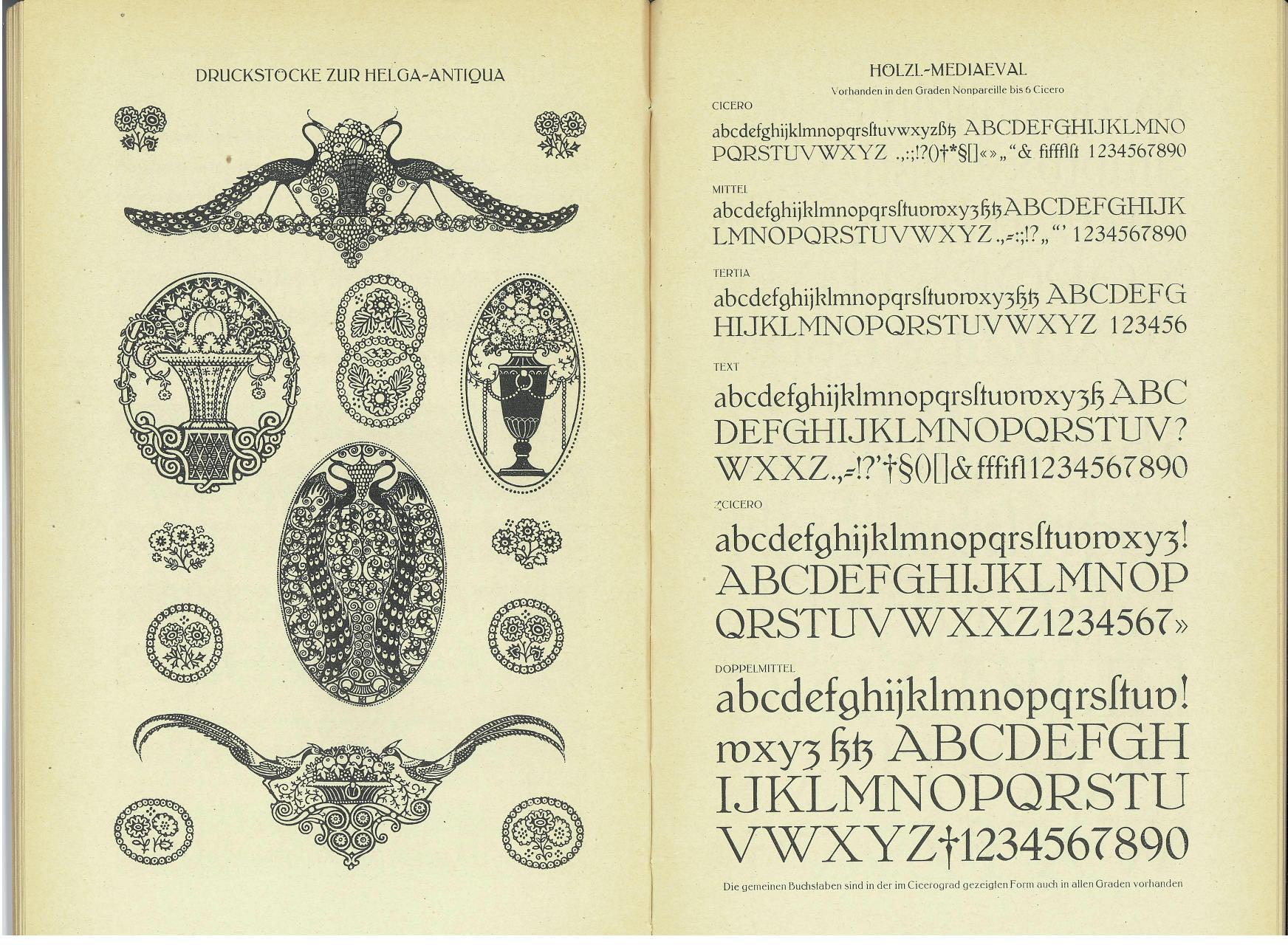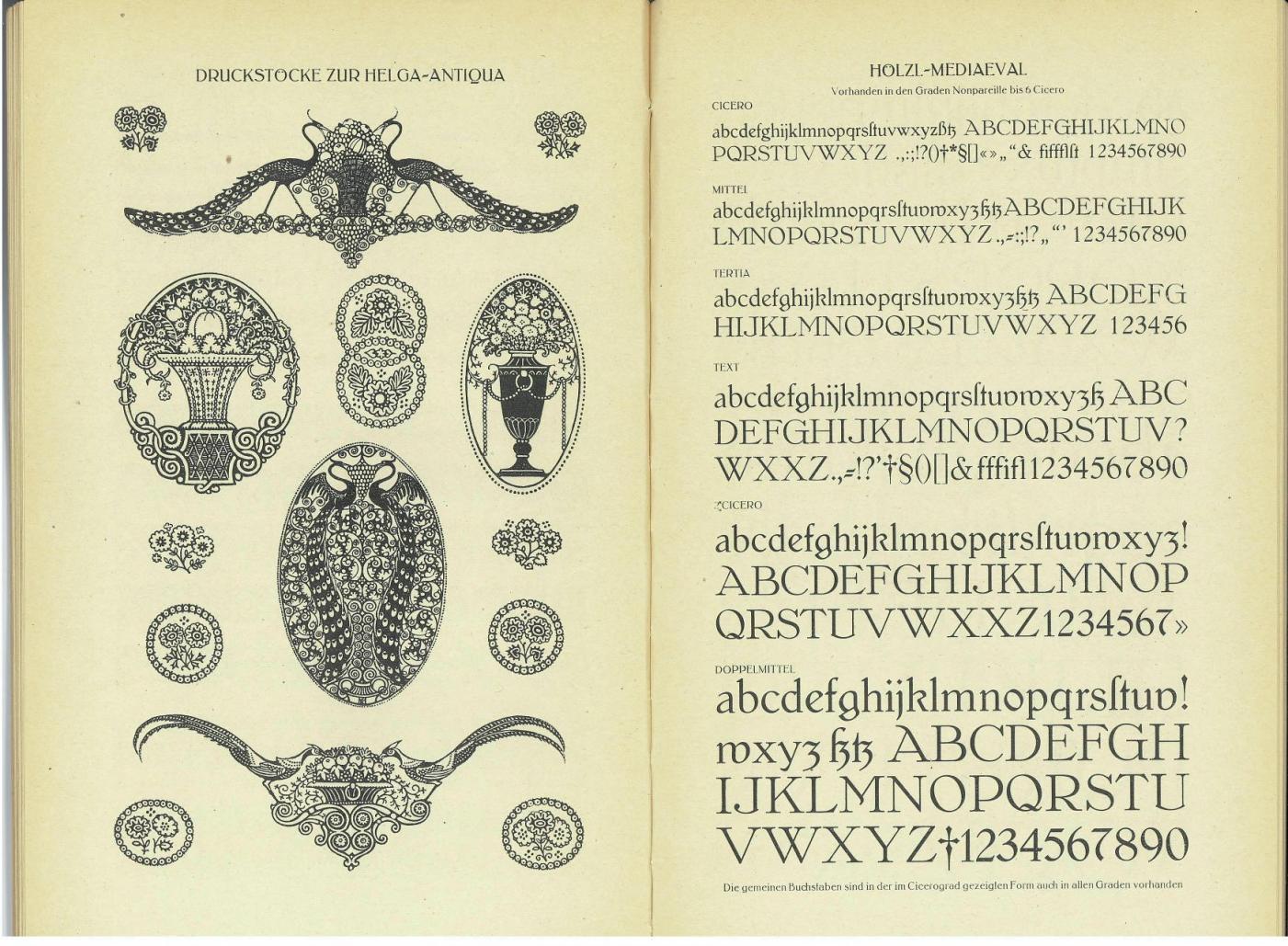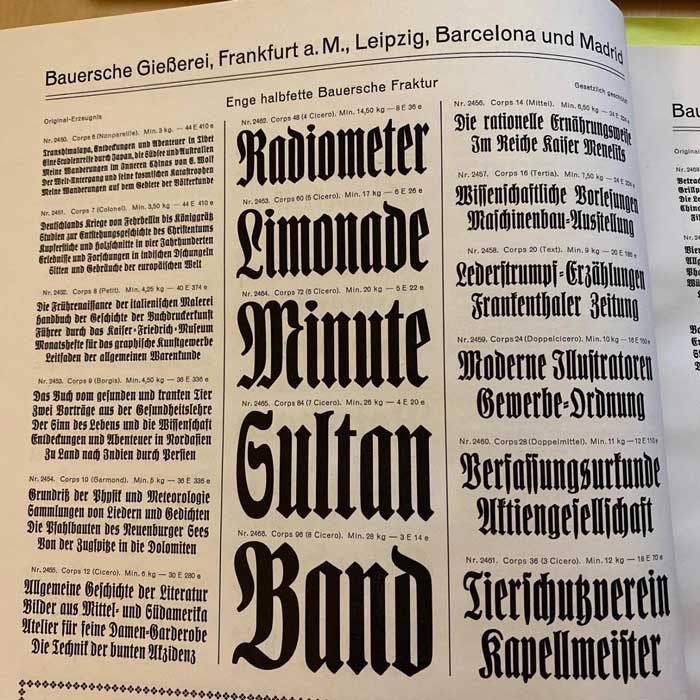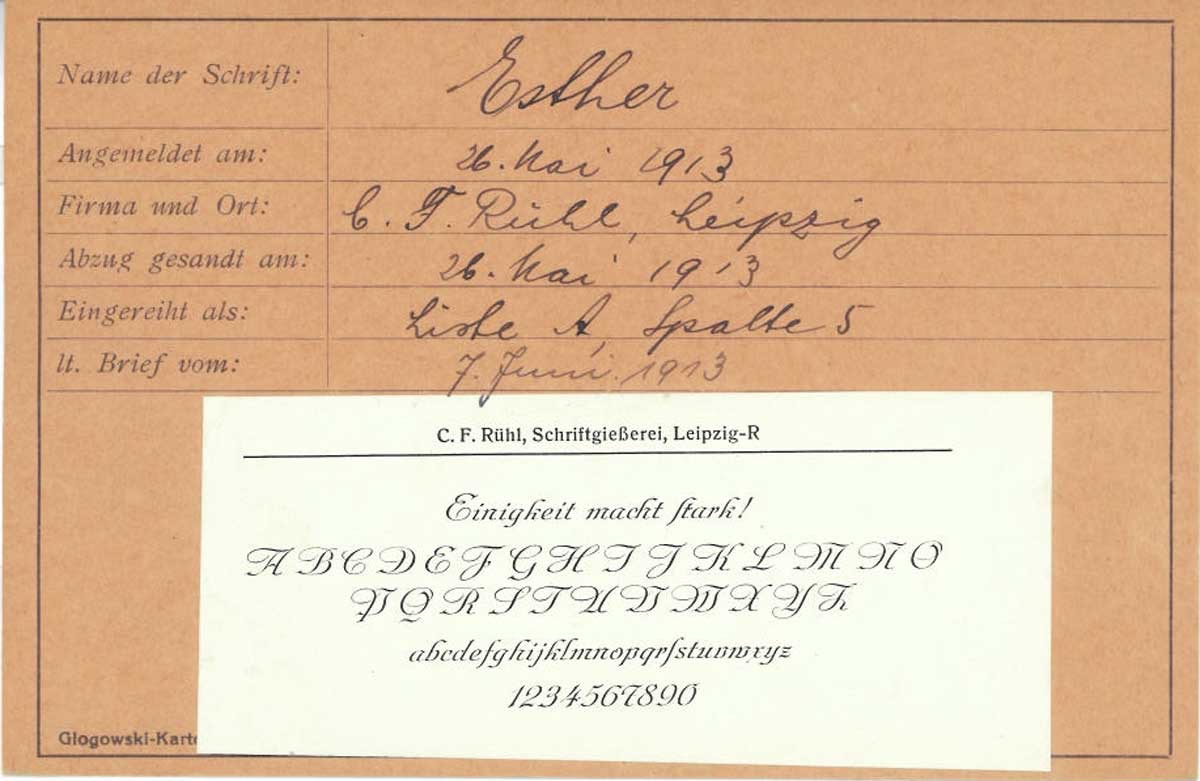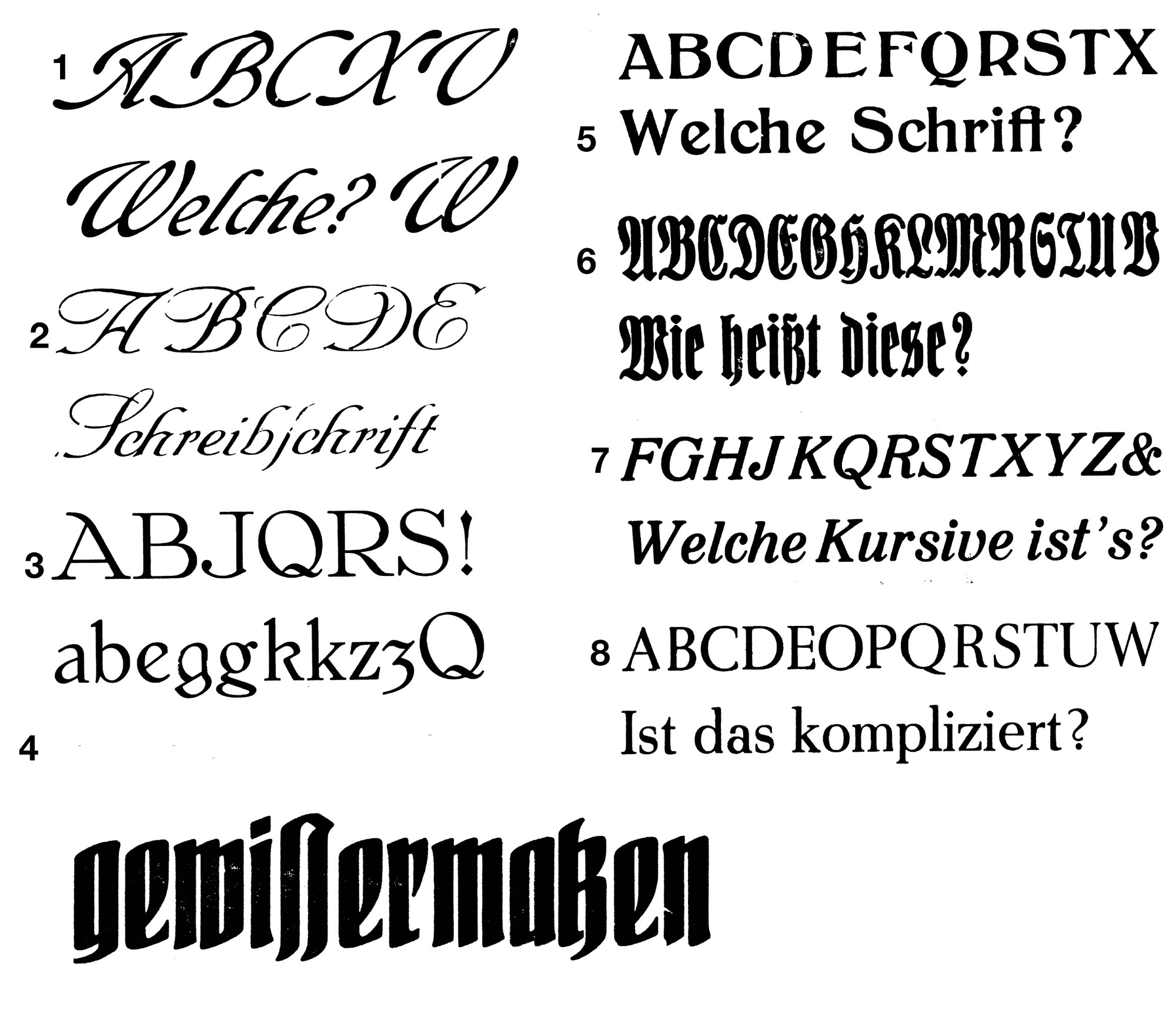
Vermutlich sehr alte Bleisatzschriften zum Identifizieren
mit diesen Schriften (aus vermutlich den Anfangsjahren des 20. Jahrhunderts) komme ich nicht wirklich zu einem Ergebnis bezüglich Schriftnamen, Gestalter, Herkunft ...
Es sind alles Bleisatzschriften in nicht wirklich tollen Zuständen, die aus verschiedenen Druckereien stammen, vorwiegend im süddeutschen Raum. Die erste ist möglicherweise die "Riedingerschrift", 3 und 5 vermutlich irgendwas aus der Ecke Ehmke/Belwe/Klinger und die 6 vermutlich irgendwas mit extraschmal und Anzeigenschrift oder so ...
Gelöst von Taurec
1 ist Riedingerschrift
Based upon Riedingerschrift, cut by Franz Riedinger for Benj. Krebs Succ. in Frankfurt am Main in 1906, here come Ridinger Std and its extended version, Ridinger Pro.
Nummer 2 ist die Esther der Schriftgießerei C. F. Rühl in Leipzig, später in den Bestand der H. Berthold AG übergegangen.
Nummer 6 ist die „Enge halbfette Bauersche Fraktur“ der gleichnamigen Bauerschen Gießerei zu Frankfurt am Main.
ich habe Nr. 8 einer Schriftensuchmaschine (whatfontis.com) vorgeworfen. Das Ergebnis war schon recht nahe:
Gmünder Antiqua:
Das ist aber nur ein Remake:
Designer: Ralph M. Unger
Ich habe keine Angaben über die Bleisatzvorlage gefunden, außer der Verweis auf eine Bleisatzvorlage.
Danke! Da steht doch aber, dass der Herr Unger die "Imprimatur" (von Bauer) als Vorbild hatte und das scheint sie mir auch wirklich zu sein ... Bleibt als spannendste Frage die Nummer 3 und das Rätsel um den schmalen Schnitt der Eldorado ...
Und ich wusste doch, dass ich Nummer 3 irgendwo schonmal gesehen habe: es ist die Hölzl Medieval der Stempel AG. Siehe Schriftmuster!